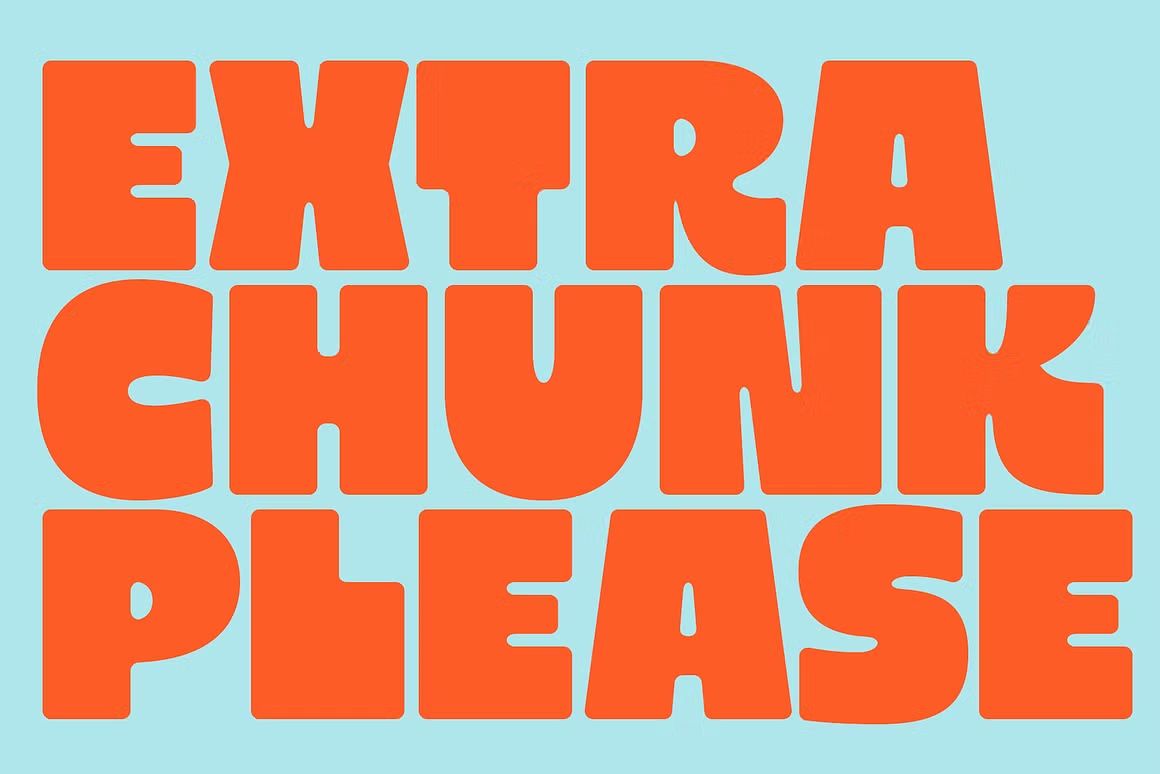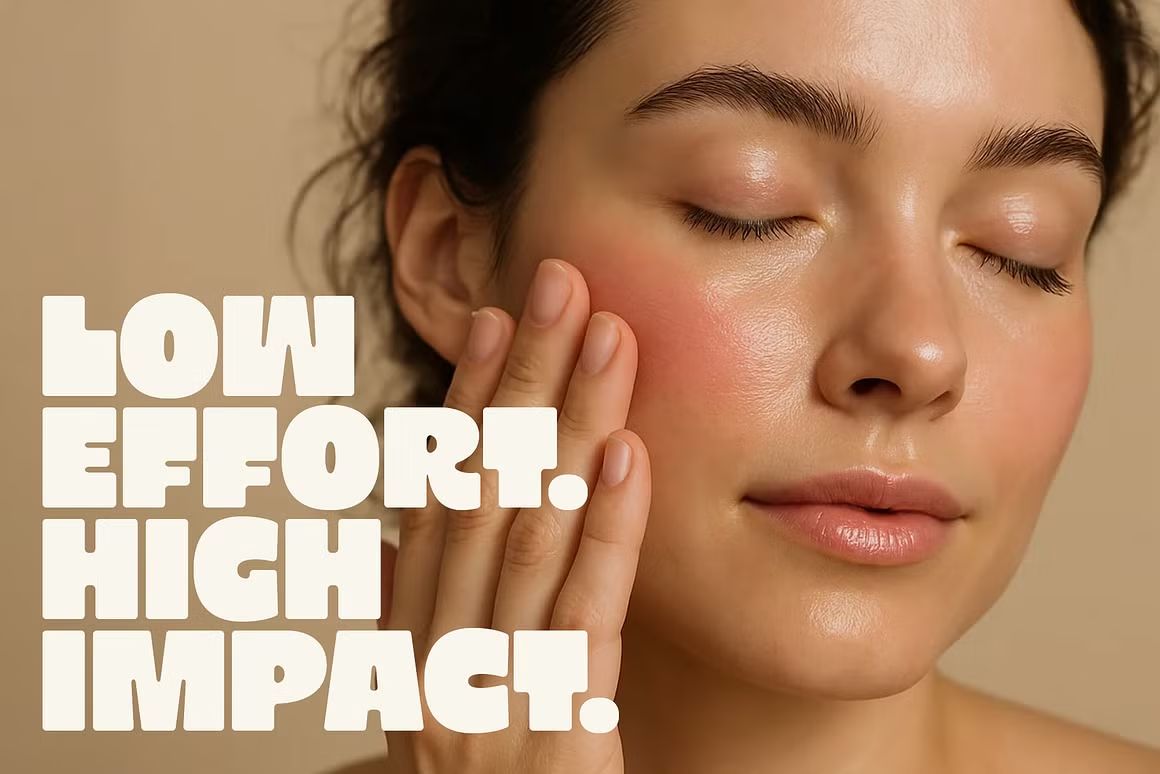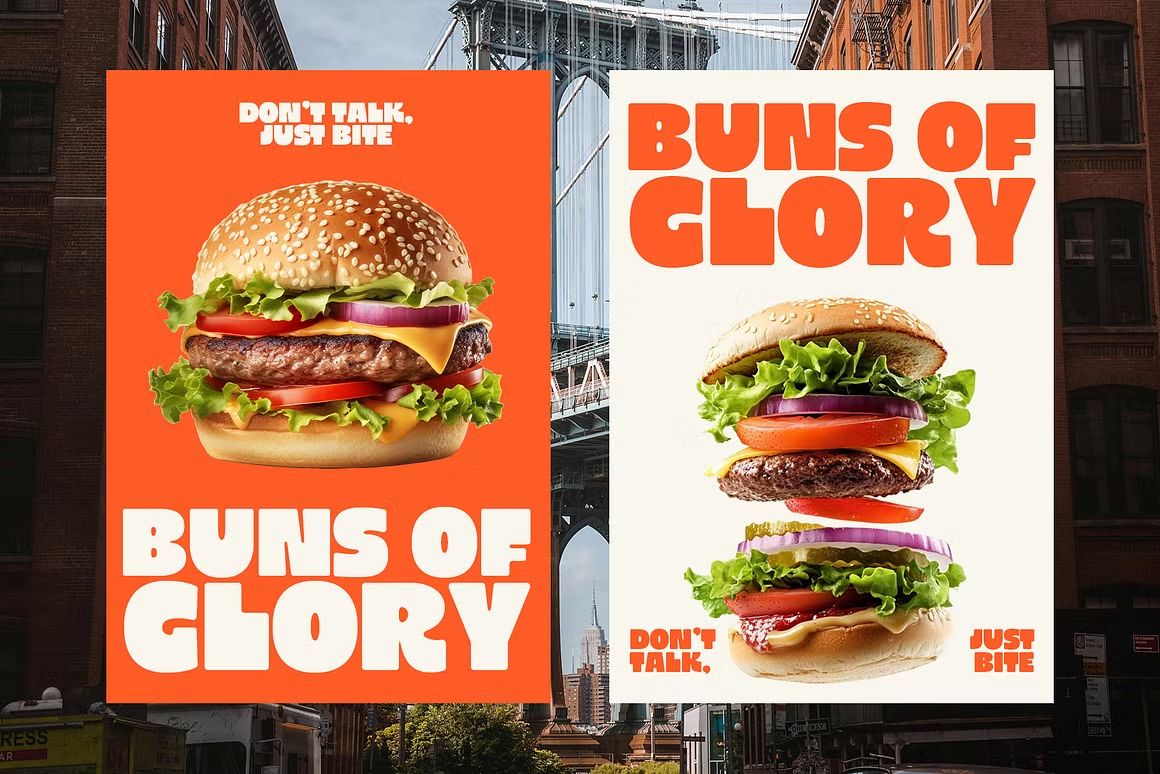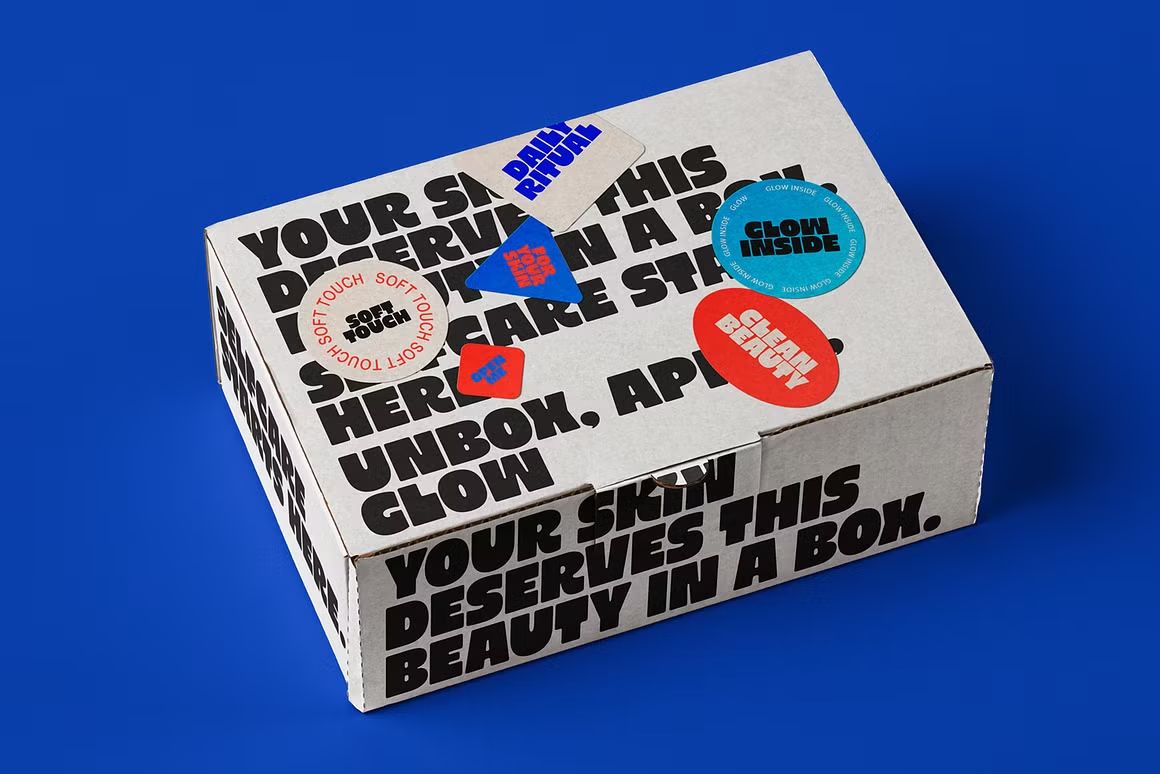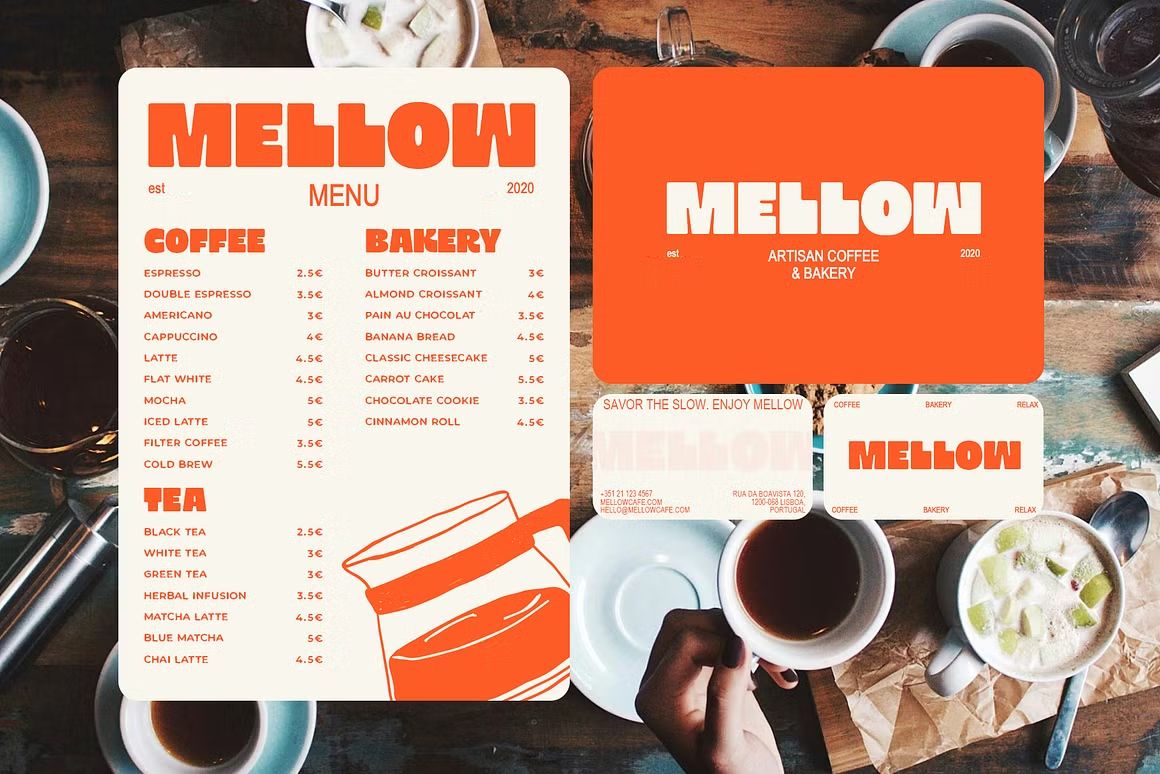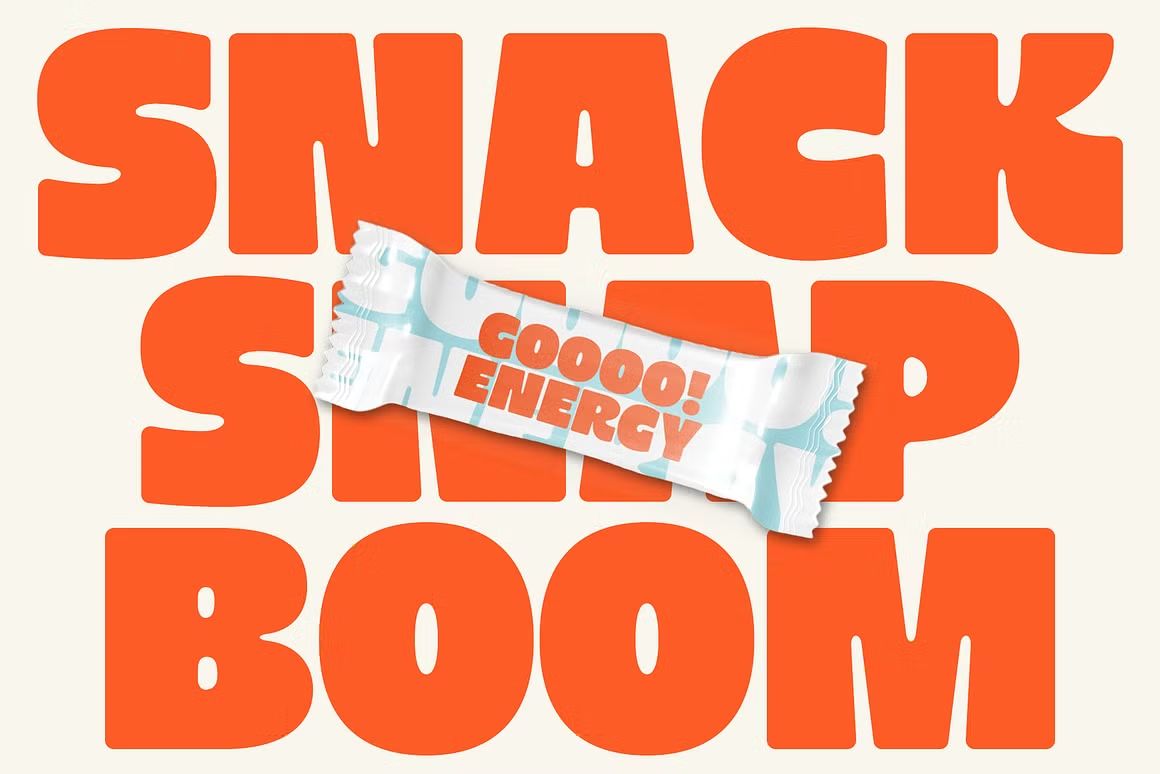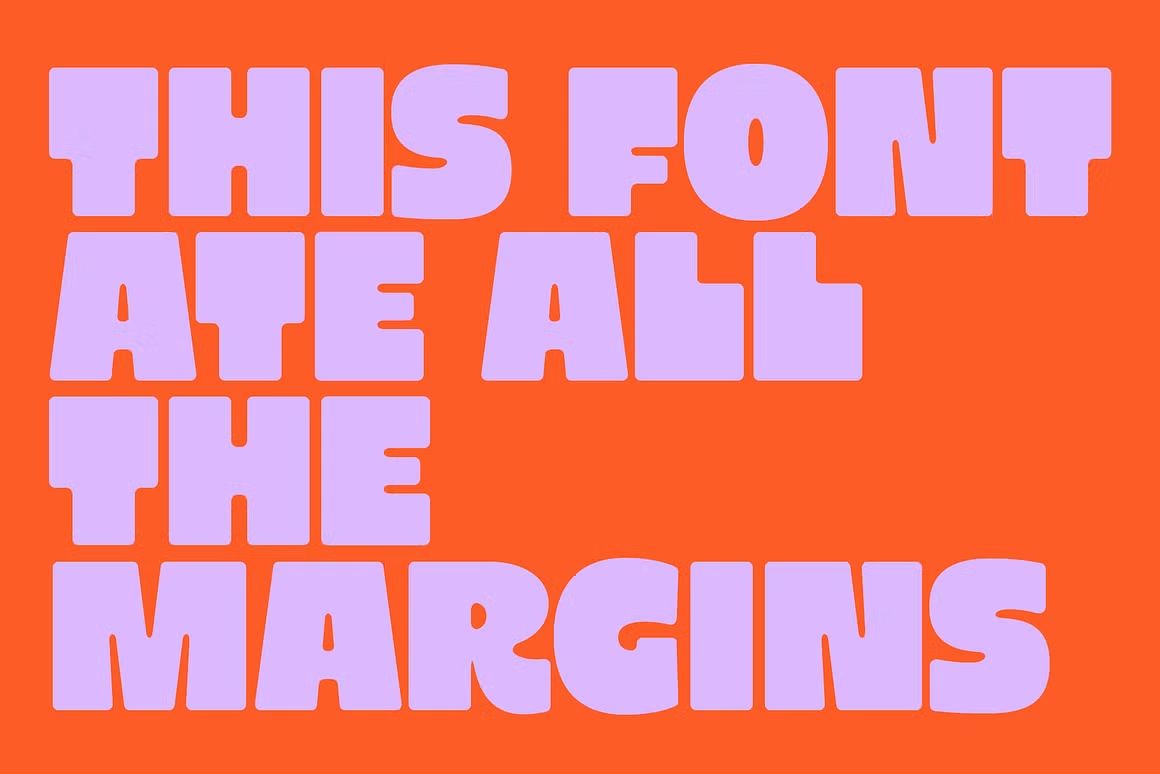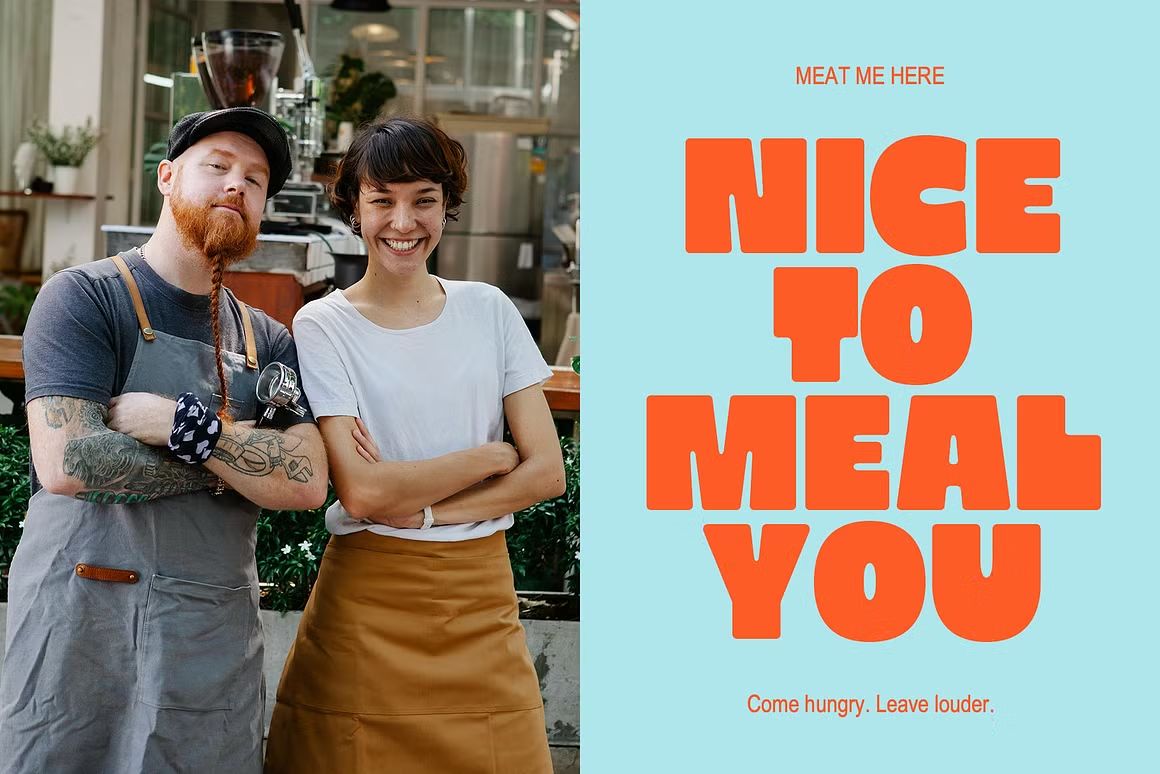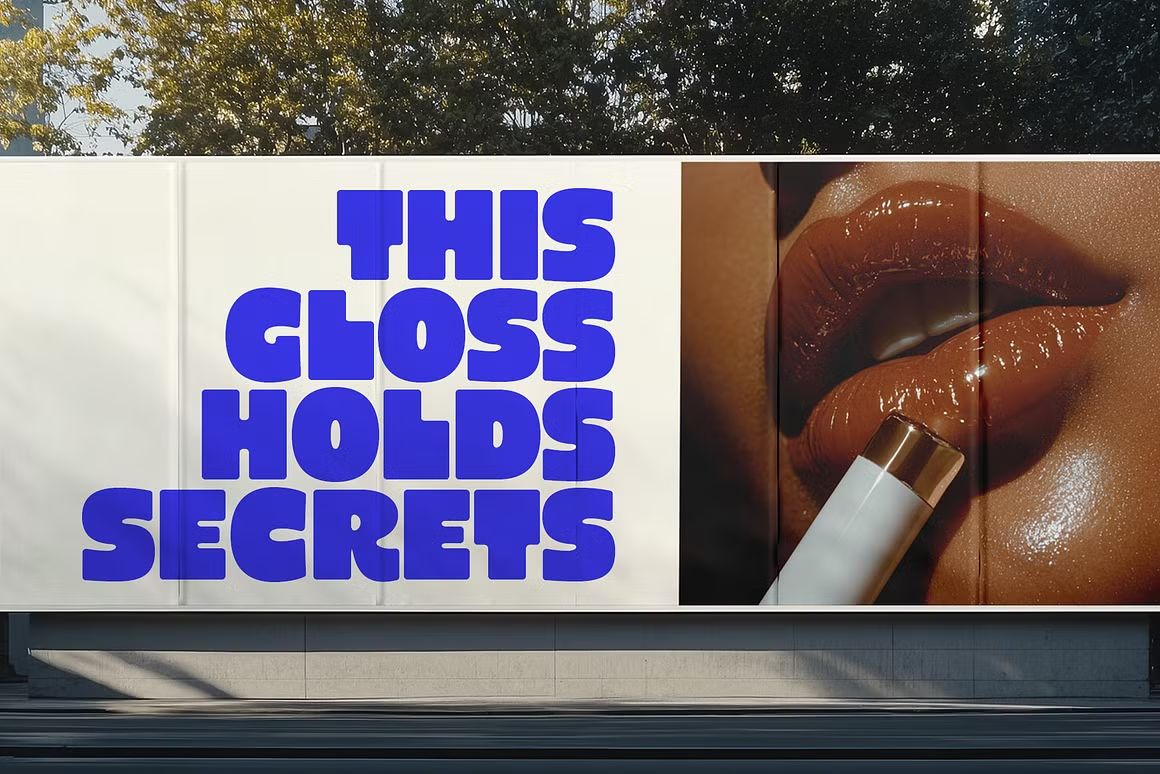
Extra Chunk Please – Ultra Bold Sans Serif Font
Extra Chunk Please adalah font sans serif ultra bold dengan karakter tebal dan kuat, cocok untuk headline, poster, logo, dan desain yang ingin tampil mencolok dan berani.
Extra Chunk Please adalah font sans serif ultra bold yang dirancang untuk memberikan kesan kuat, modern, dan mencolok. Sangat cocok digunakan untuk headline, poster, branding, logo, dan berbagai kebutuhan desain yang membutuhkan tampilan visual yang tegas dan menonjol. Dengan bentuk huruf yang solid dan proporsi seimbang, font ini memberikan dampak maksimal dalam sekali lihat.
Fitur unggulan:
• Gaya ultra bold yang tebal dan mencolok
• Cocok untuk headline, logo, poster, dan branding
• Huruf kapital, angka, dan tanda baca lengkap
• Ideal untuk proyek cetak maupun digital